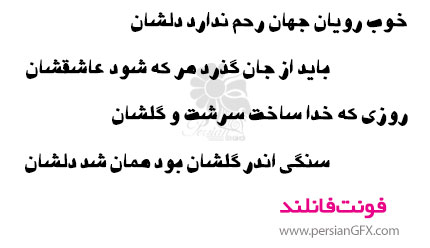
فونت فان لند برپایه قلم یاقوت طراحی شده است که شکلی بسیار فانتزی به خود گرفته و برای برخی پوستر های کودکانه در جملات کوتاه و عنوان ها مناسب است در نسخه اول این فونت نقطه ها به صورت لوزی بود که در نسخه بعدی برای بدست آوردن شکل فانتزی بهتر نقطه ها به صورت دایره طراحی شده اند.